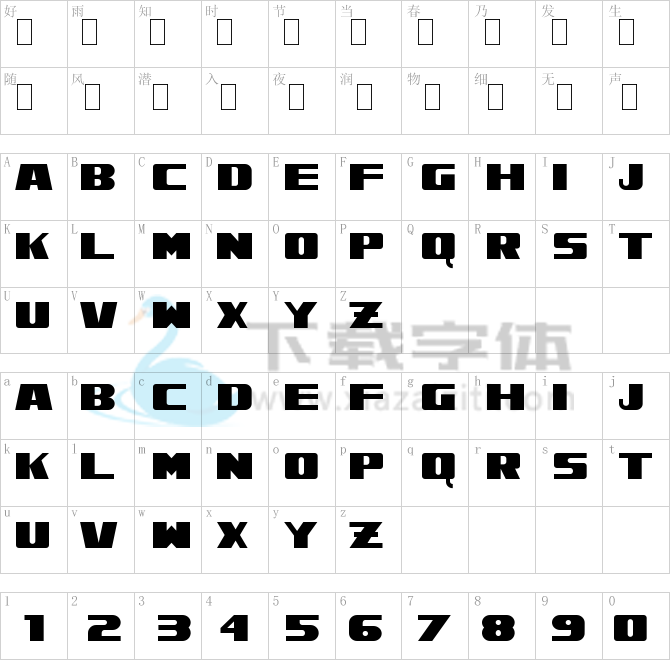
Alpenkreuzer.ttf字体下载,这款字体结构工整、笔画清晰,兼顾美观与易读性,适用于标题、正文、海报、包装、LOGO 等多种场景。字形优雅稳定,风格百搭耐看,适配日常排版与创意设计,让文字呈现更舒适、更具质感。Alpenkreuzer.ttf字体下载一笔一画,皆是细节,以均衡的比例、流畅的线条打造舒适视觉体验,字形端正大气,风格简约现代。无论是商业设计、品牌宣传还是日常排版,都能轻松驾驭,让文字更有格调与力量。Alpenkreuzer.ttf字体下载字体下载。
• 字体名称:Alpenkreuzer